4. Januar 2006: Intel tritt mit einer neuen Hausschrift auf, einer modifizierten Neo Sans (interner Name: »Neo Sans Intel«). Das Vorbild wurde 2004 von Sebastian Lester entworfen. Der Mix aus Dax und DIN macht Schule, viele Marken und Unternehmen folgen in den darauf folgenden Monaten.
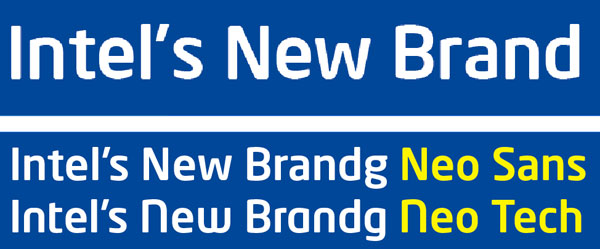
6. Januar 2006. FontShop hat seine Räume nach Schriften benannt. Der Konferenzraum heißt »Scala«, der Massageraum »Balance«, das Rauchkabuff »Nebulae« und die Denkzelle »Beowolf«. Letztere diente im Januar 2006 Ausstellungsraum für den Jahresrückblick der FontShop-Marketingabteilung. Nie zuvor war sie produktiver.
Der aufmerksame Fontblog-Leser microboy erkennt auf einem Foto eine Drucksache, die er noch nie zuvor gesehen hatte (hier sein Kommentar) … kein Wunder, das fonts Extra »Script« war noch druckfrisch. Es wurde damals auch als erste FontShop-Drucksache zum Download angeboten. Die Links im Beitrag funktionieren nicht mehr, aber das Magazin liegt heute natürlich auf Issuu:
fonts Extra »Script«: Am 13. Januar erschien erstmals eine FontShop-Drucksache auf Papier und digital
12. Februar 2006. FontShop bringt einen Free-Fonts auf den Markt, der für Wirbel sorgt. Er heißt Trivia und sieht der Schrift der Fußballweltmeisterschaft 2006 verdammt ähnlich. Heute darf ich beichten: Diese Ähnlichkeit war durchaus beabsichtigt. Mit der kostenlosen Schrift Trivia (Design: Henning Krause) wollte FontShops seine Corporate-Font-Kompetenz demonstrieren – also eine Exklusivschrift nach einem fiktiven Briefing zu erstellen –, und den Fußballfreunde im Land eine WM-Schrift für private Zwecke schenken. Nicht zuletzt war Trivia eine Antwort auf den Lizenzwahn der Fifa, die den Medien vorschreiben wollte, Fussball statt Fußball zu schreiben und die Verwendung des offiziellen WM-Logos sogar für redaktionelle Zwecke untersagte.
6. März 2006. Mitte Januar 2006 baten wir die Fontblog-Leser um Namensvorschläge für unsere beiden TYPO-Kätzchen, die gerade auf www.typoberlin.de eingezogen waren. Es kamen wunderbare Vorschläge, wie zum Beispiel Erik & Rike (Oliver Adam), Holly & Golightly (HD), Adrian & Gerrit (Gerrit), Tyra & Tycho (Chris) oder Jekyl & Hyde (Luke). Am besten gefiel uns dann der Vorschlag von robertmichael: Copy & Paste.
24. April 2006. Von März bis Ende April entlarve ich 127 Fußball-WM-Trittbrettfahrere, also Unternehmen und Marken, die inoffiziell mit der Weltmeisterschaft werben. Dann gebe ich auf. Es sind noch 50 Tage bis zur Fußball WM, und täglich schießen neue Fußball-Produkte wie Pilze aus dem Boden. Ich hätte die Leser-Empfehlung zu Beginn meiner Serie Ernst nehmen sollen: »… schreib’ lieber über die Firmen, die jeden Bezug zur WM vermeiden.«
5. Mai 2006. Erstmals gibt es für eine TYPO-Konferenz eigens komponierte und produzierte Musik. Sie wird für Jingles, Zwischentitel, die spätere DVD, den Abschlussfilm, als Pausenmusik, einen Video-Podcast und zum täglichen Mitsingen (TYPO-Hymne) eingesetzt. Die 4 Demos à 40 Sekunden hören sich auch heute noch gut an:
25. Juni 2006. Die beste 100-Beste-Plakate-Ausstellung aller Zeiten ist auf dem Gelände des Berliner Spreebogens aufgebaut. Damals schrieb ich: »Ich habe selten eine Ausstellung erlebt, wo Form und Inhalt so harmonisch einhergingen. Jahrelang durfte man die 100 besten Plakate in einem umgebauten Bibliotheks-Foyer am Schlossplatz bewundern: muffig und düster. Erst in diesem Jahr zogen sie in den öffentlichen Raum. Und dann auch noch in den spannendsten, den Berlin gerade zu bieten hat. Einen Steinwurf vom neuen Hauptbahnhof entfernt liegt der Spreebogenpark, in dessen Rasenflächen sich zwei rostige Stahlwände hineinschneiden wie gigantische Gemüsemesser.«
30. Juni 2006. Ganz Deutschland ist im Fußballfieber … das Sommermärchen läuft auf Hochtouren. Auf die FontShop-Marketing-Leiterin Kathrin Kluge ist infiziert. Sie hatte sich 8 Wochen vor der WM mit ihrem Freund Thomas um Karten für das Viertelfinale beworben. Nun war der Tag gekommen: Deutschland – Argentinien.
Drei Stunden vor dem Anpfiff präpariert sich Kathrin für das vielversprechende Spiel, mit Farbe, Shirt, Tröte und Fähnchen. 30 Kolleginnen und Kollegen müssen leider zu Hause bleiben und fernsehgucken ….
9. Juli 2006. Fontblog wird zum ersten Mal politisch. Die Berliner Gestalterin, TYPO-Sprecherin und FontShop-Beirat-Mitglied Juli Gudehus stolpert über die Spielregeln des Designpreis der Bundesrepublik Deutschland 2007. Mit einem offenen Brief an Wirtschaftsminister Michael Glos (auch veröffentlicht in PAGE 8/2006) versucht sie dem Preis für den Preis auf die Spuren zu kommen. Es hagelt 50 Kommentare, HD Schellnack und Juli streiten sich vehement. Noch sind die Kommentare hier zu lesen, nächste Woche schaltet Haloscan sie ab … das Internet vergisst doch!
Wie schnell die Zeit vergeht! So schnell kann man sich Schriften übersehen – oder täuschen wir uns und die NeoSans erschien schon damals so charakterlos?